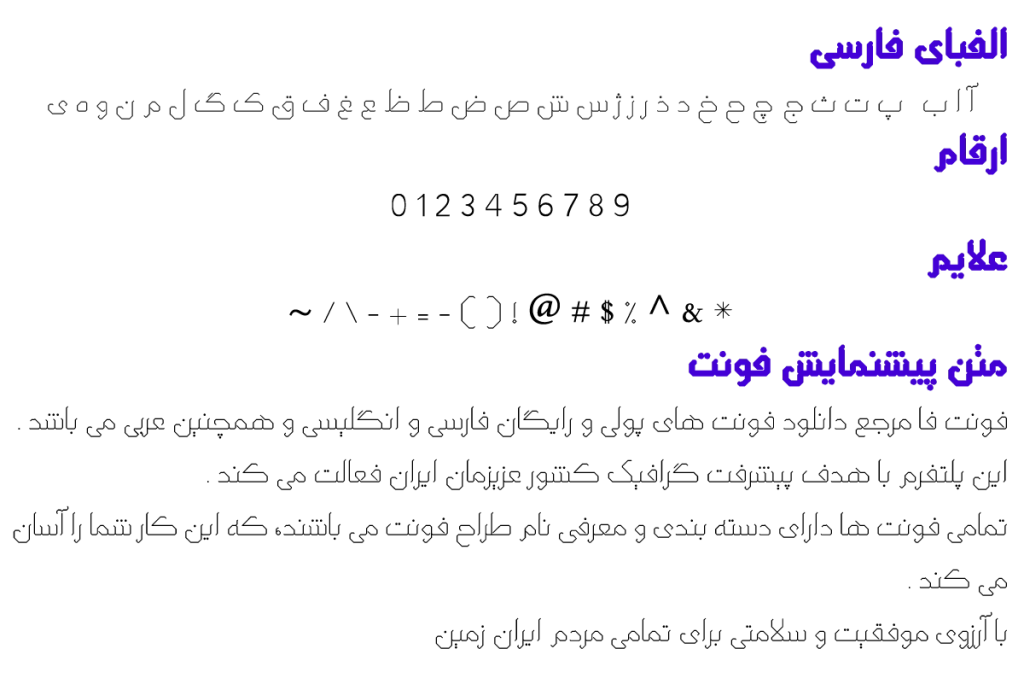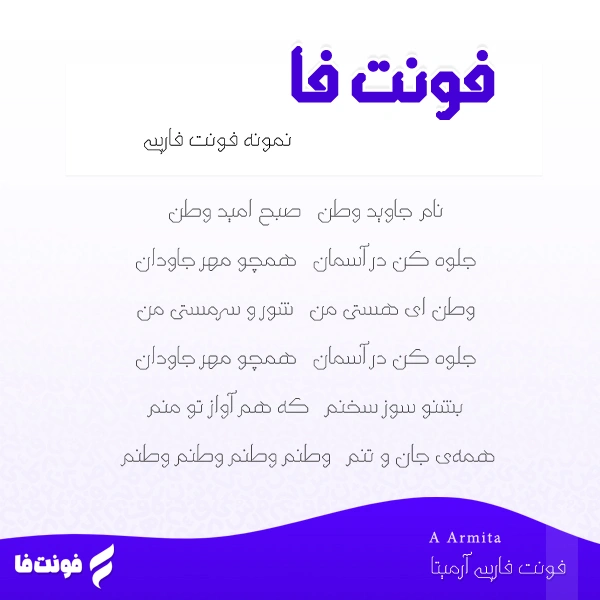
فونت فارسی آرمیتا – A Armita
توضیحات و معرفی فونت آرمیتا
فونت فارسی آرمیتا ( A Armita ) از مجموعه فونت های آزاد می باشد، همینطور نوع فونت فانتزی می باشد.
همینطور فونت A Armita در 2 وزن سنگین و سبک است.
- A Armita Black
- A Armita Light
در تصویر زیر، شعر کهن «وطنم» با این تایپفیس به نمایش گذاشته شده است.